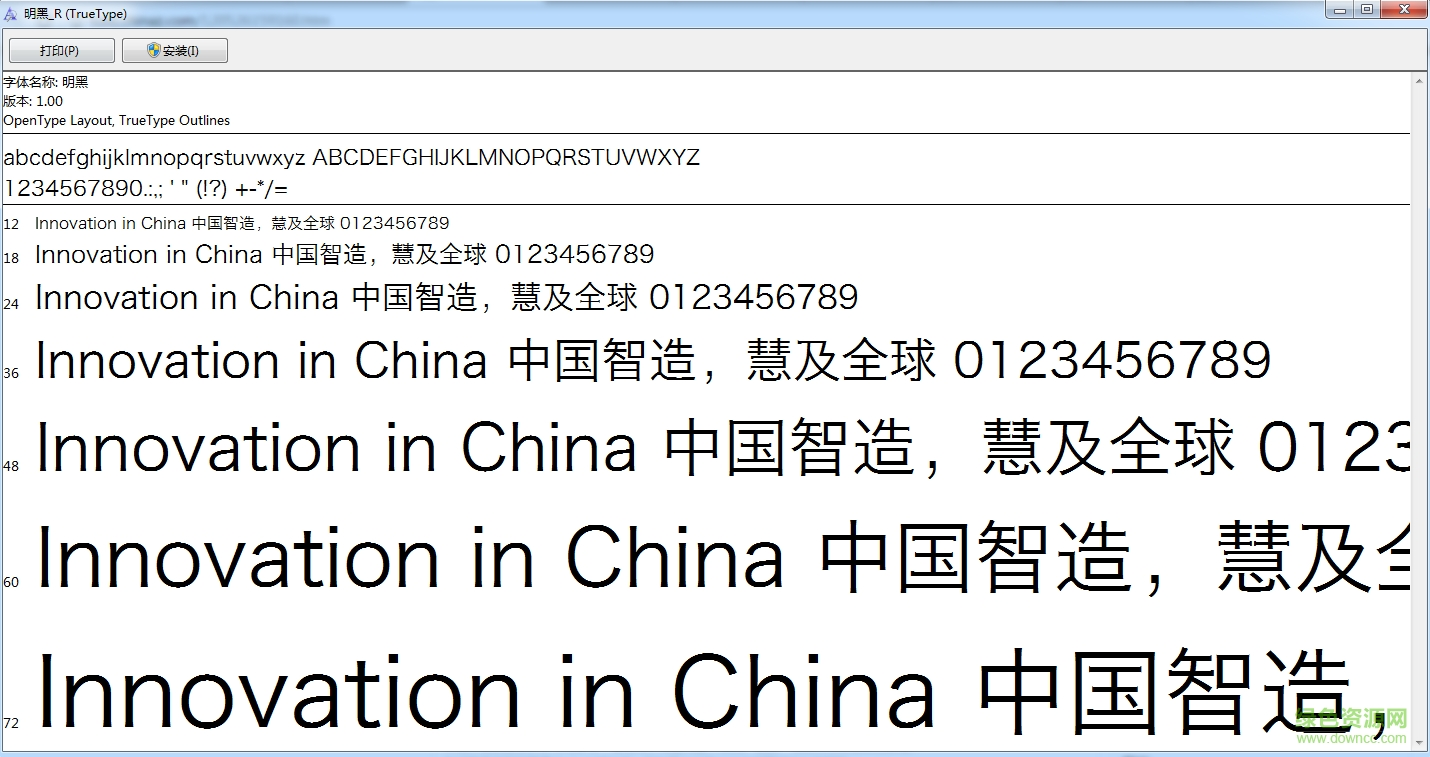
明黑_R字體是一款應(yīng)用廣泛的黑體字體,該字體樸素規(guī)范,筆畫(huà)粗細(xì)勻稱,整體方方正正,清晰明朗,非常耐看,歡迎小伙伴下載使用!
黑體是中文一類字體的名稱,與白體相反,特點(diǎn)是沒(méi)有襯線裝飾,筆劃粗壯有力,撇捺等筆畫(huà)不尖,使人易于閱讀,由于其醒目的特點(diǎn),常用于標(biāo)題,導(dǎo)語(yǔ),標(biāo)志等等。